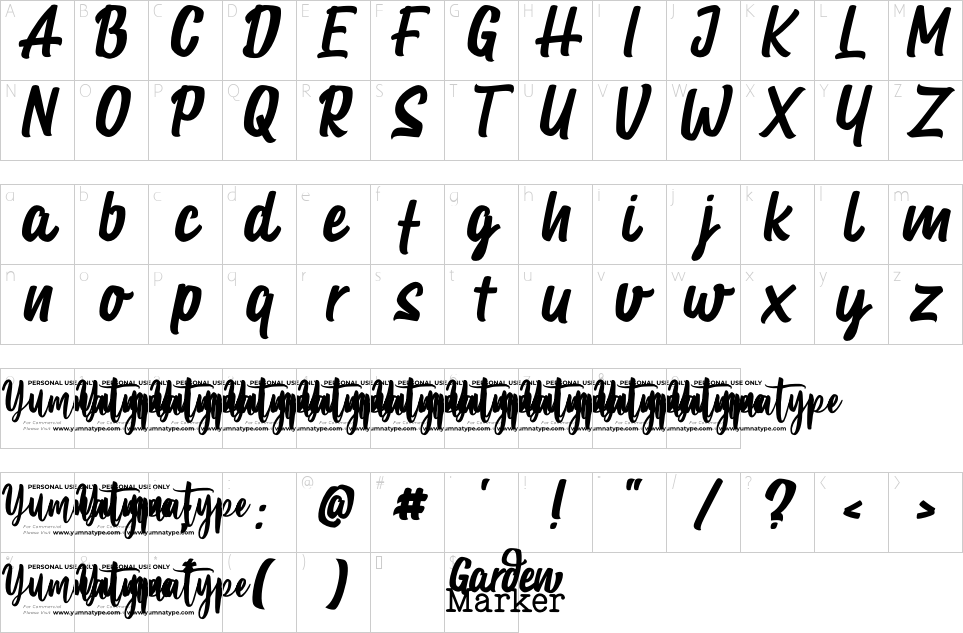
Garden Marker Font – Fonte Grátis
Garden Marker Font
Descubra a tranquilidade e a simplicidade que a Garden Marker font oferece para seu próximo projeto visual. Esta elegante fonte foi cuidadosamente criada por Yumna Type, projetada especificamente para facilitar a escrita de rótulos de jardins ou qualquer aplicação que exija um estilo simples e confiável. Com sua aparência clara e legível, ela não apenas tornará seu trabalho mais eficiente, mas também dará vida à arte gráfica de seu projeto. Sua simplicidade e facilidade de uso a tornam uma escolha ótima para quem procura fontes gratuitas, sem comprometer na qualidade ou elegância. Com Garden Marker font, você não precisará se preocupar com custos adicionais, pois ela está disponível de graça para Windows e Mac. Não há dúvida de que esta é uma fonte perfeita tanto para designers profissionais quanto para iniciantes, buscando um toque natural em seu trabalho visual.